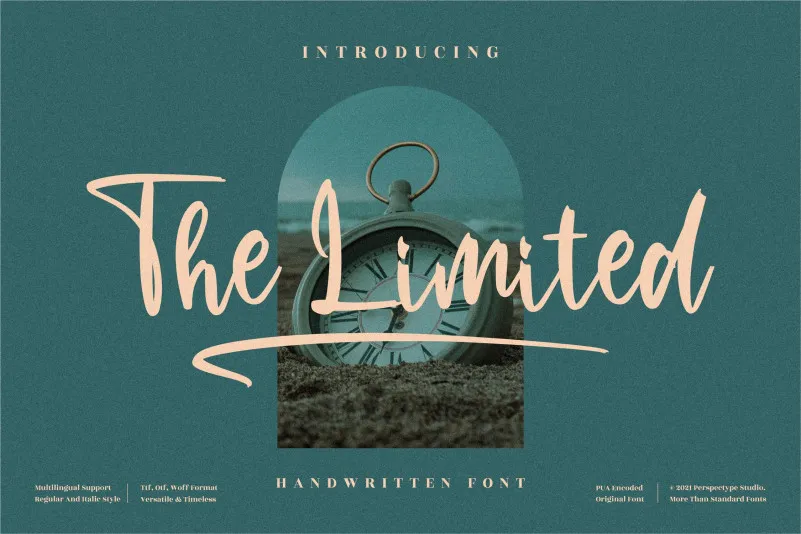
The Limited Font – Fonte Grátis
The Limited Font
A “The Limited Font” é uma elegante tipografia script que exala sofisticação e refinamento. Esta fonte foi especialmente criada para quem busca um olhar delicado e encantador em seus projetos gráficos, oferecendo um ar de frescura e beleza ao seu trabalho. Perfeita para aqueles buscando uma mudança leve nas suas composições, a “The Limited Font” é uma escolha excelente para designers que desejam dar um toque delicado à sua arte visual. Seja em cartazes, editoriais ou qualquer outro formato de criação gráfica, esta fonte certamente fará sua marca com seu design refinado e sedutor.